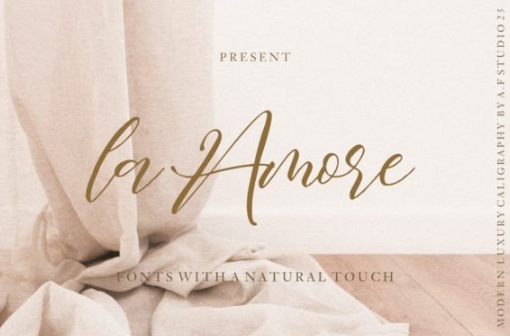
[Creativefabrica] La Amore Font (2022)
La Amore - это соврСмСнный каллиграфичСский ΡˆΡ€ΠΈΡ„Ρ‚ с прСкрасным элСгантным стилСм. Он идСально ΠΏΠΎΠ΄Ρ…ΠΎΠ΄ΠΈΡ‚ для Π±Ρ€Π΅Π½Π΄ΠΈΠ½Π³Π°, Π»ΠΎΠ³ΠΎΡ‚ΠΈΠΏΠΎΠ², ΠΏΡ€ΠΈΠ³Π»Π°ΡˆΠ΅Π½ΠΈΠΉ, Π³Π»Π°Π², ΠΊΠ°Π½Π²Ρ‹, свадСб, ΠΎΠ΄Π΅ΠΆΠ΄Ρ‹ ΠΈ ΠΌΠ½ΠΎΠ³ΠΎΠ³ΠΎ Π΄Ρ€ΡƒΠ³ΠΎΠ³ΠΎ.